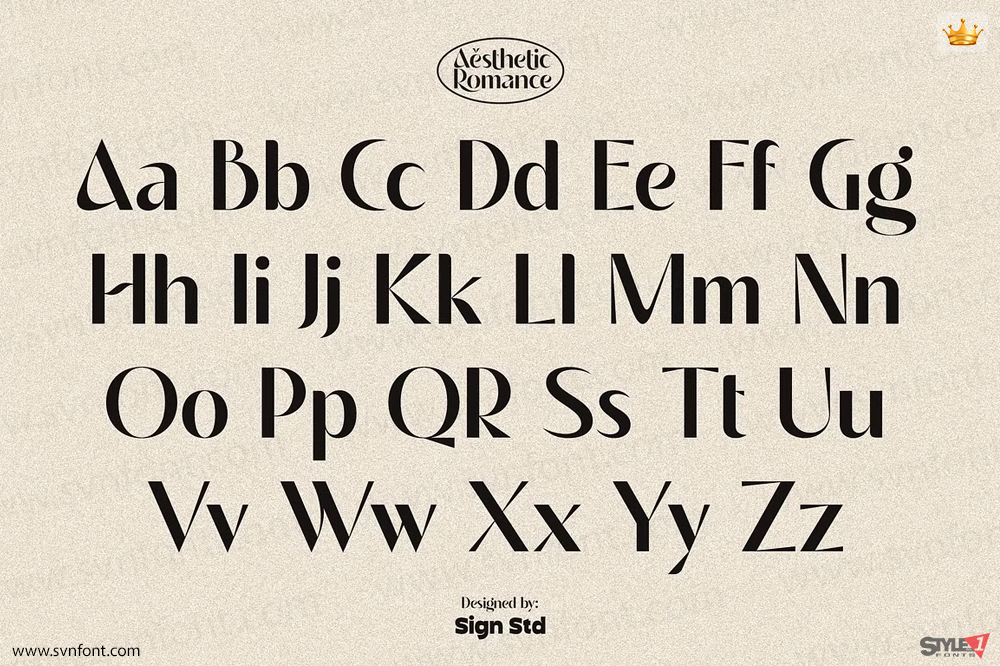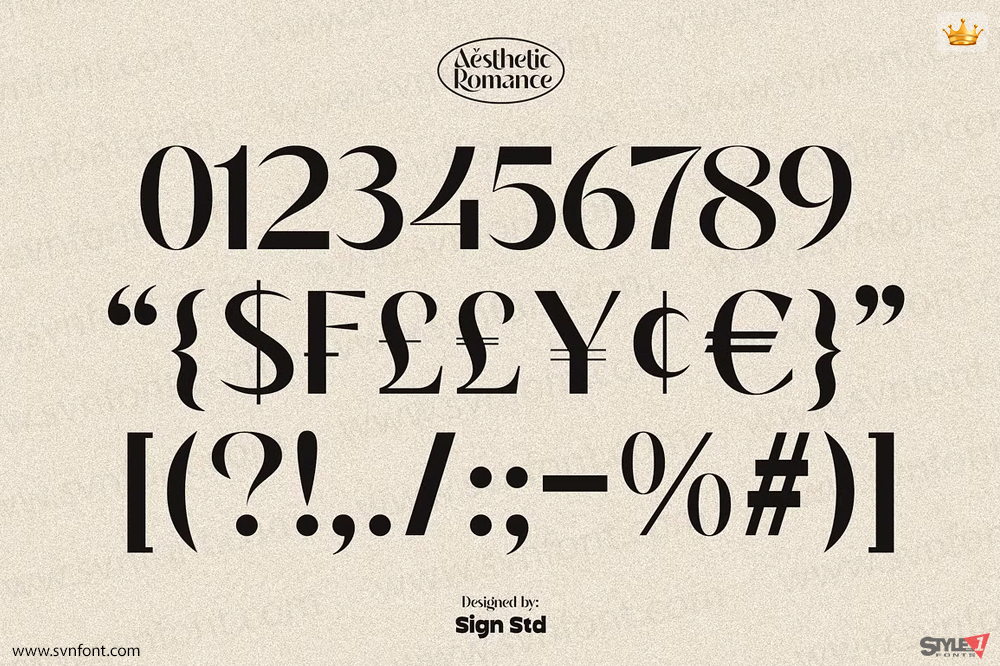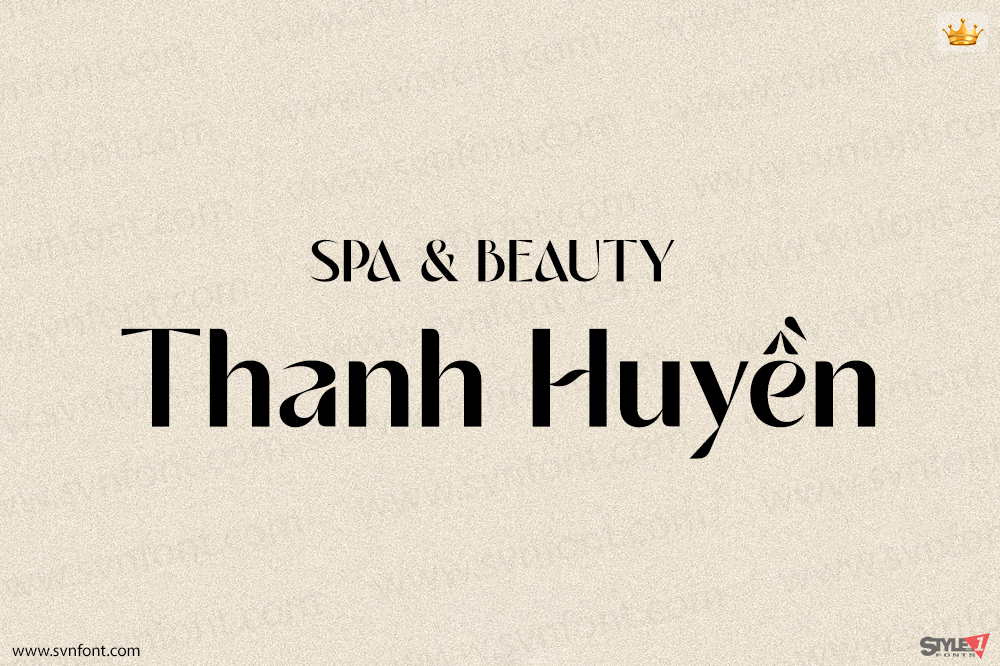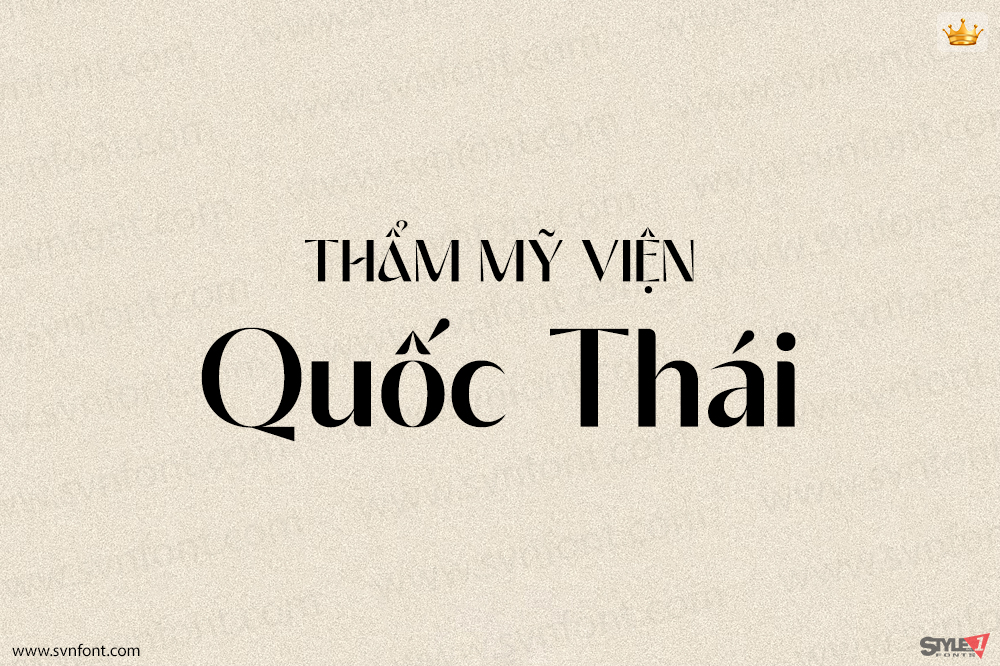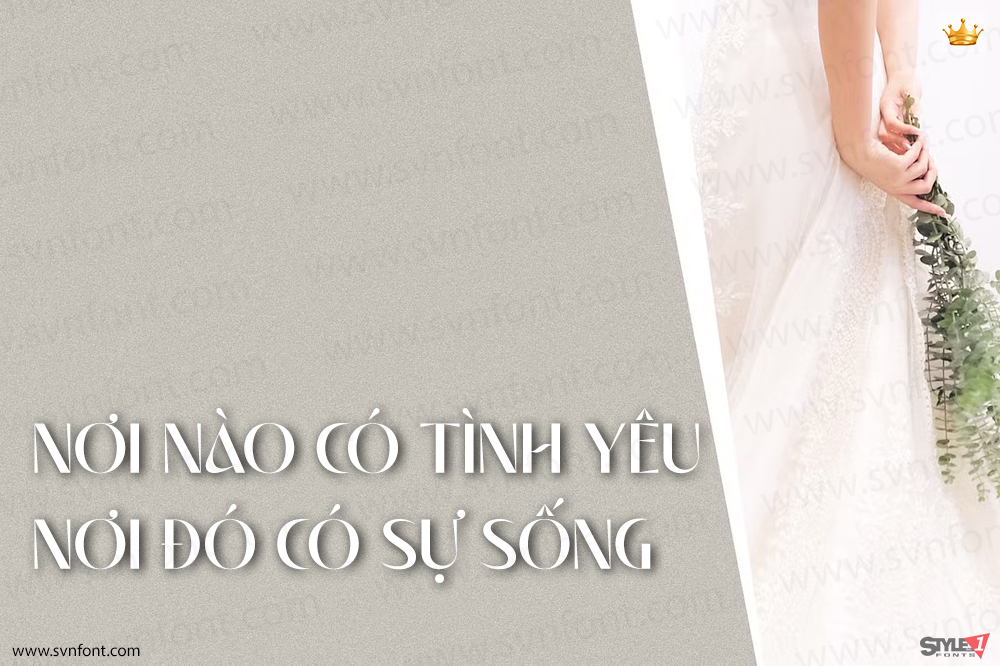
Sign Studio giới thiệu một phông chữ mới mang phong cách đẹp và lãng mạn. “Aesthetic Romance” có độ dày vừa phải, điều này có nghĩa là nó có thể đa năng cho cả việc viết chú thích lẫn hiển thị tiêu đề. Phông chữ này được trang bị các ký tự chữ ghép đẹp mắt và các ký tự thay thế. Nó sẽ hoàn hảo cho bất kỳ thiết kế nào về tiêu đề, tiêu đề trang, xây dựng thương hiệu, nhãn mác, tạp chí, áp phích và nhiều hơn nữa.